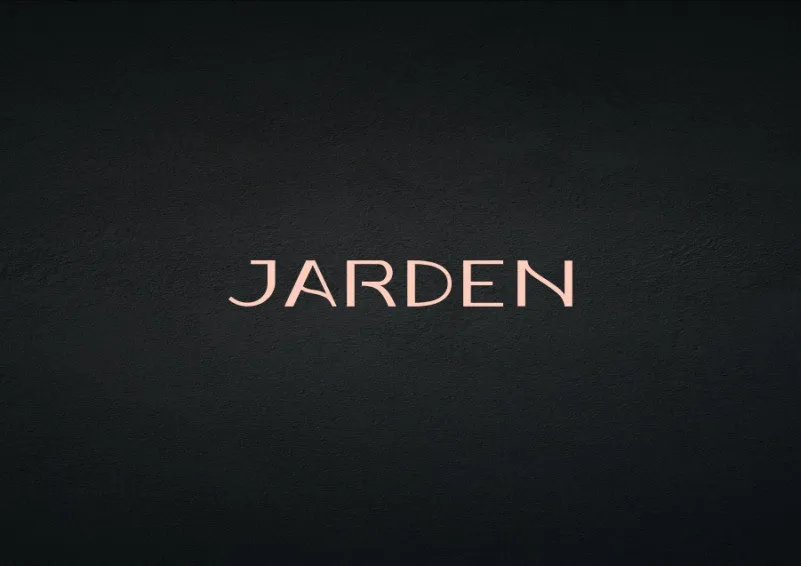
A JARDEN Sans Serif é uma parte da família de tipos moderna e forte criada por Artsigma Design. Esta fonte impressiona nos tamanhos de exibição, tornando-a ideal para uso em logotipos ou capas, enquanto manter sua leitura fácil mesmo em textos maiores. O design dos triângulos no tipo e as formas distintivas das letras mostram claramente a força que essa fonte pode ter em projetos de logotipos e editoriais ambiciosos. Seja para um site profissional ou uma campanha publicitária criativa, JARDEN Sans Serif oferece um estilo limpo e moderno que se adapta perfeitamente tanto para uso em grandes tamanhos quanto para textos menores, fazendo dela uma opção versátil e elegante para qualquer projeto visual.